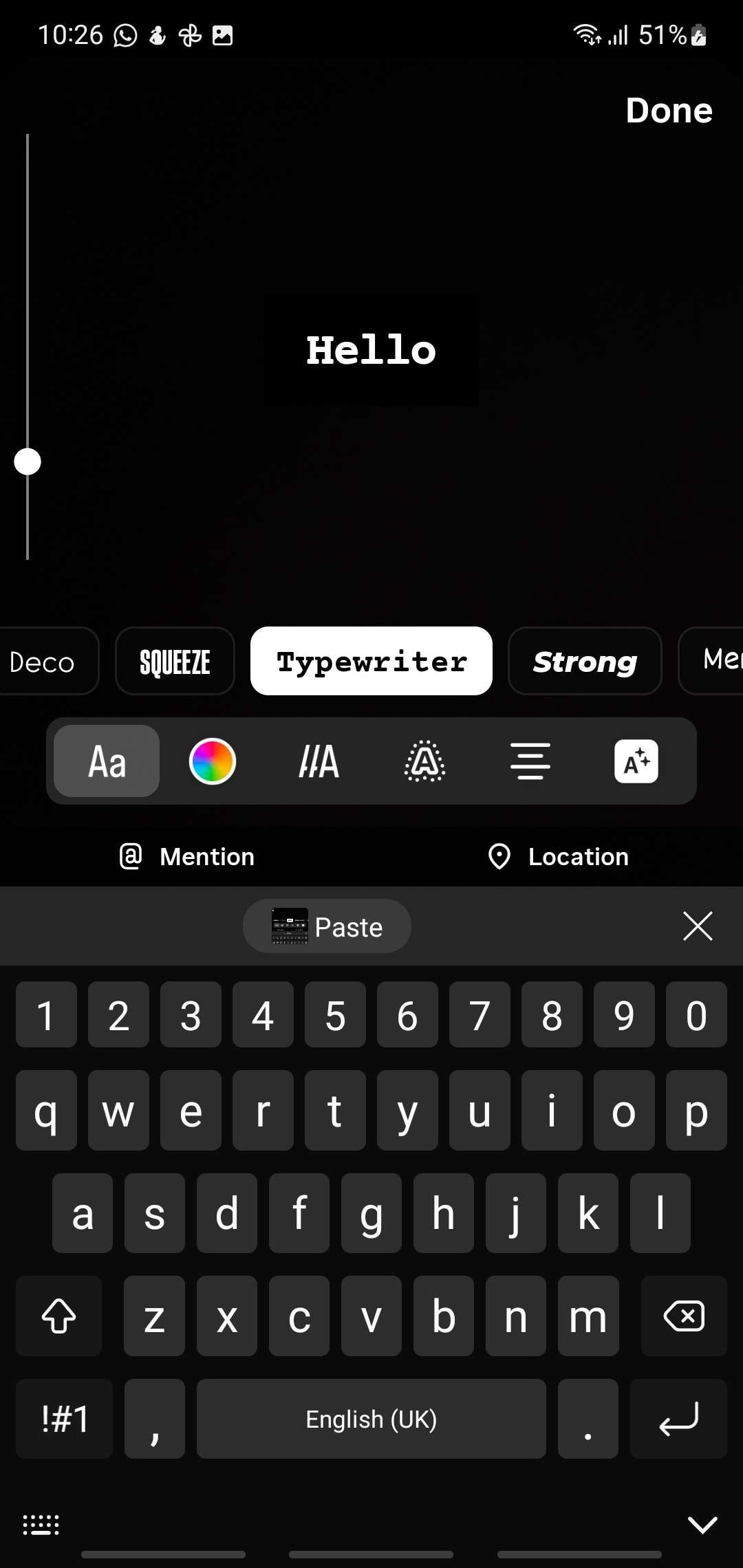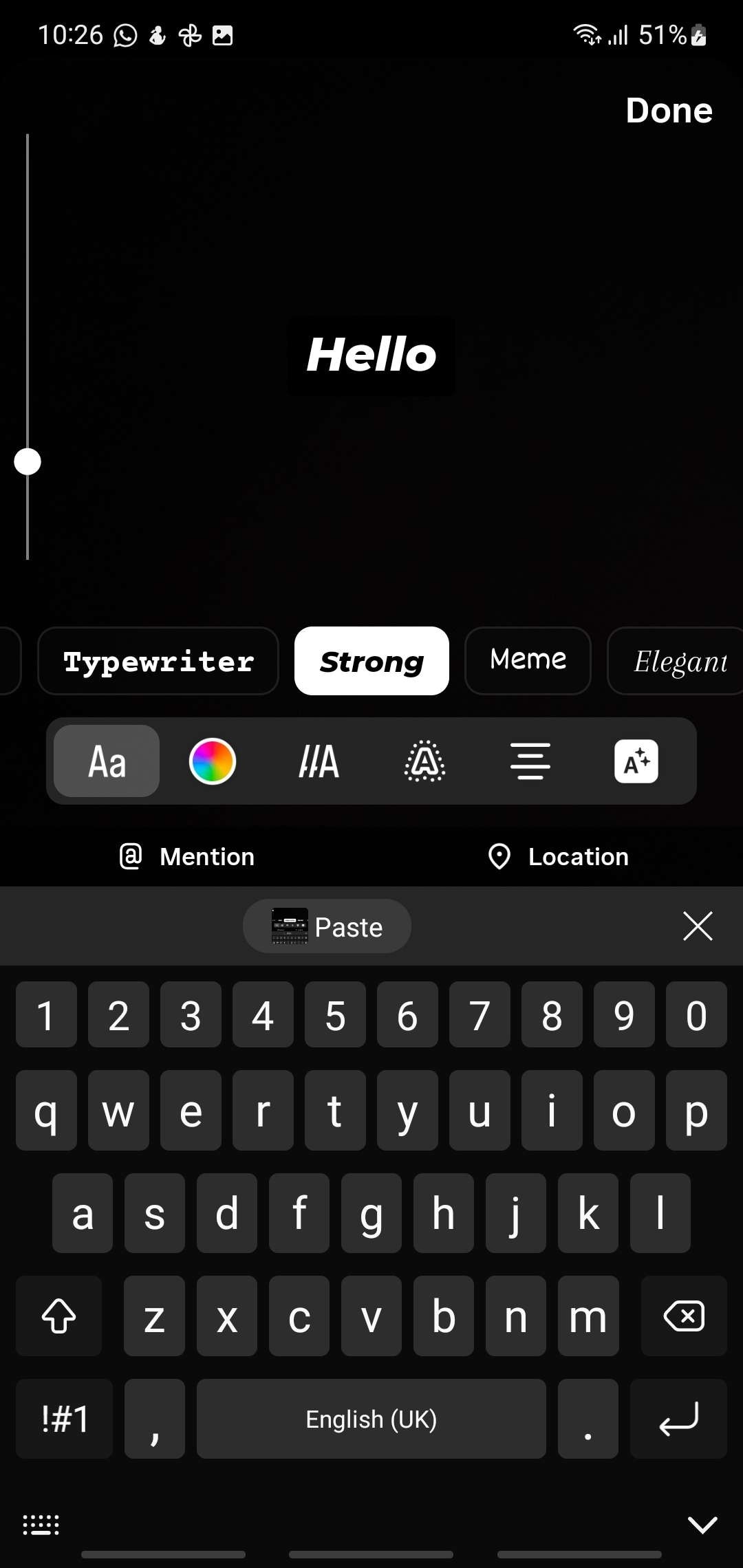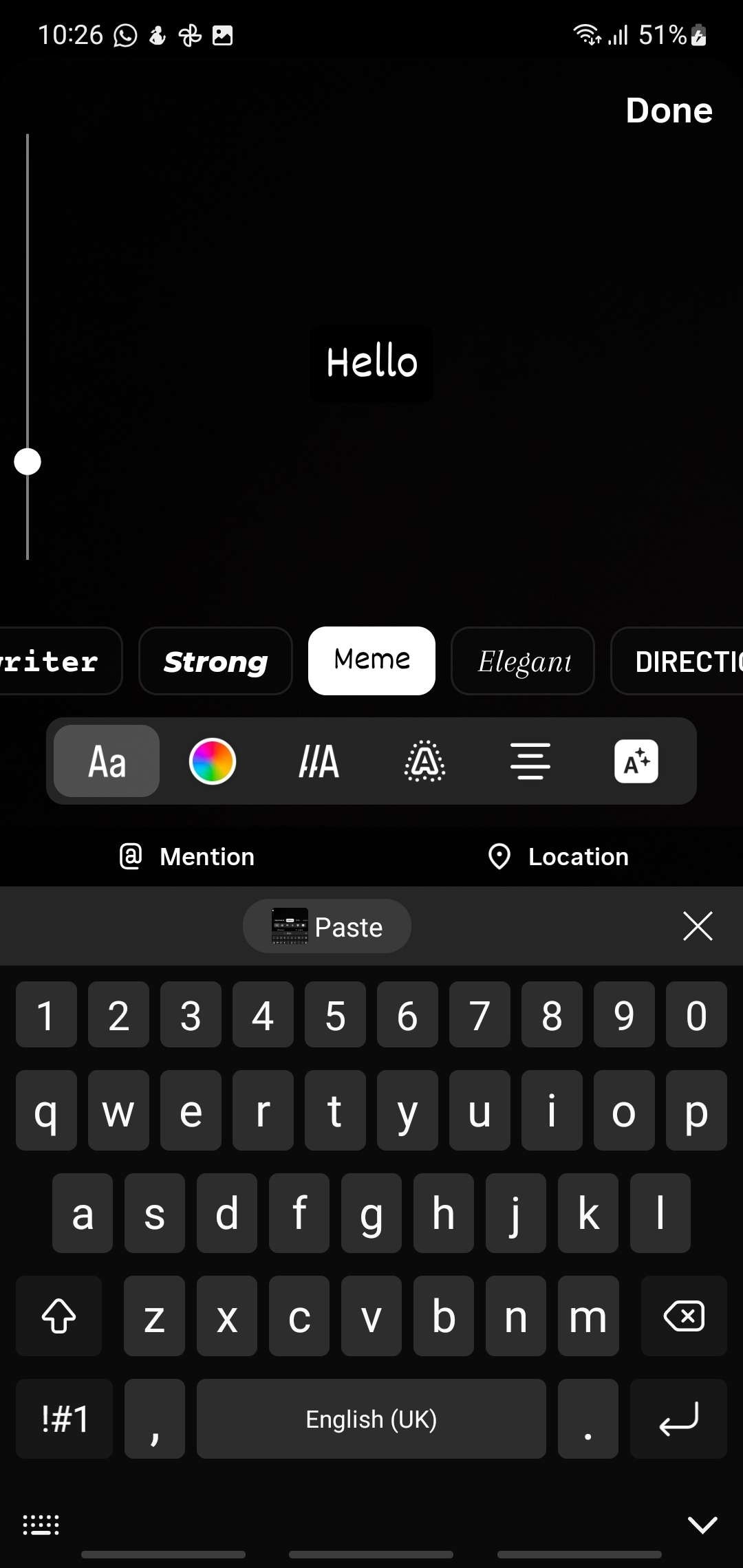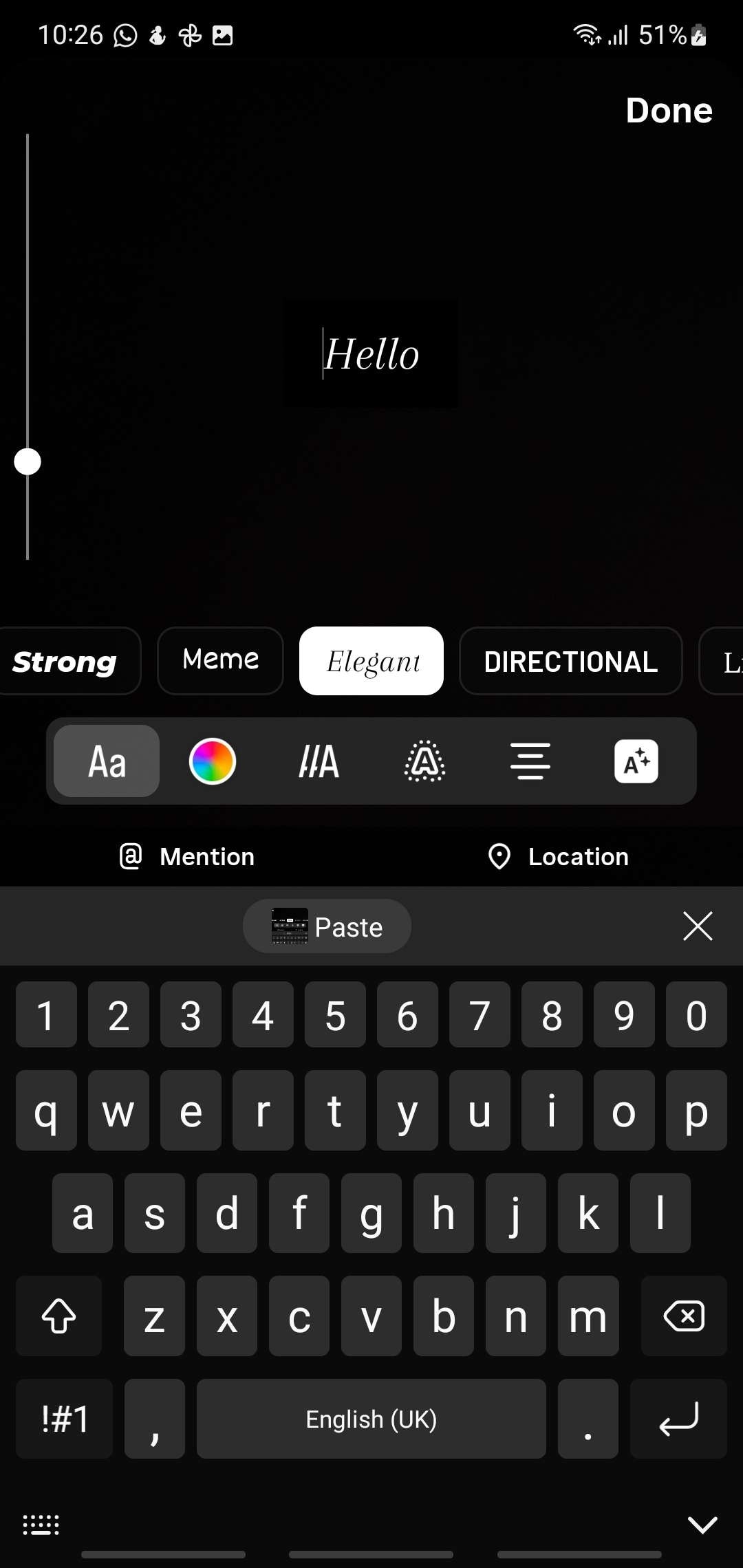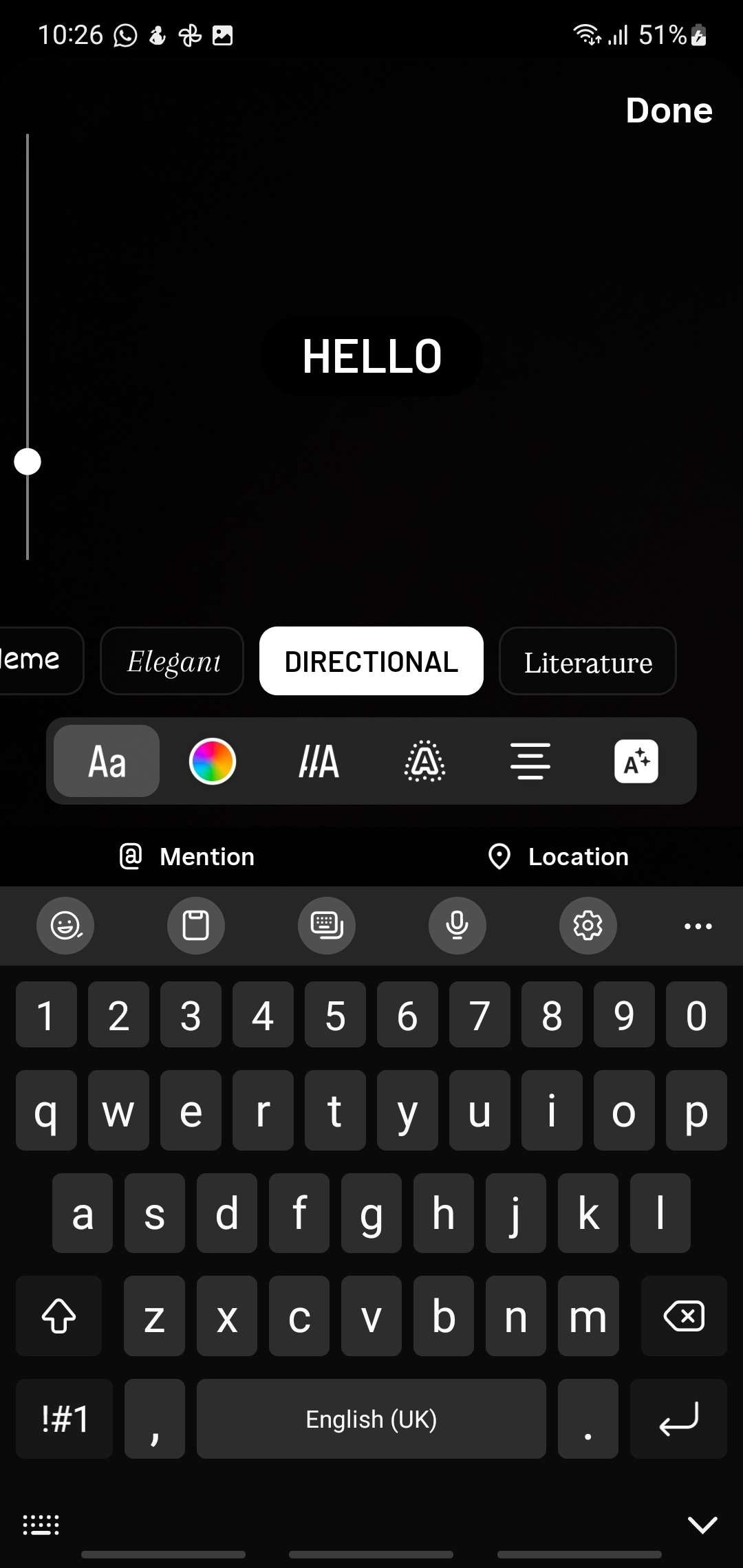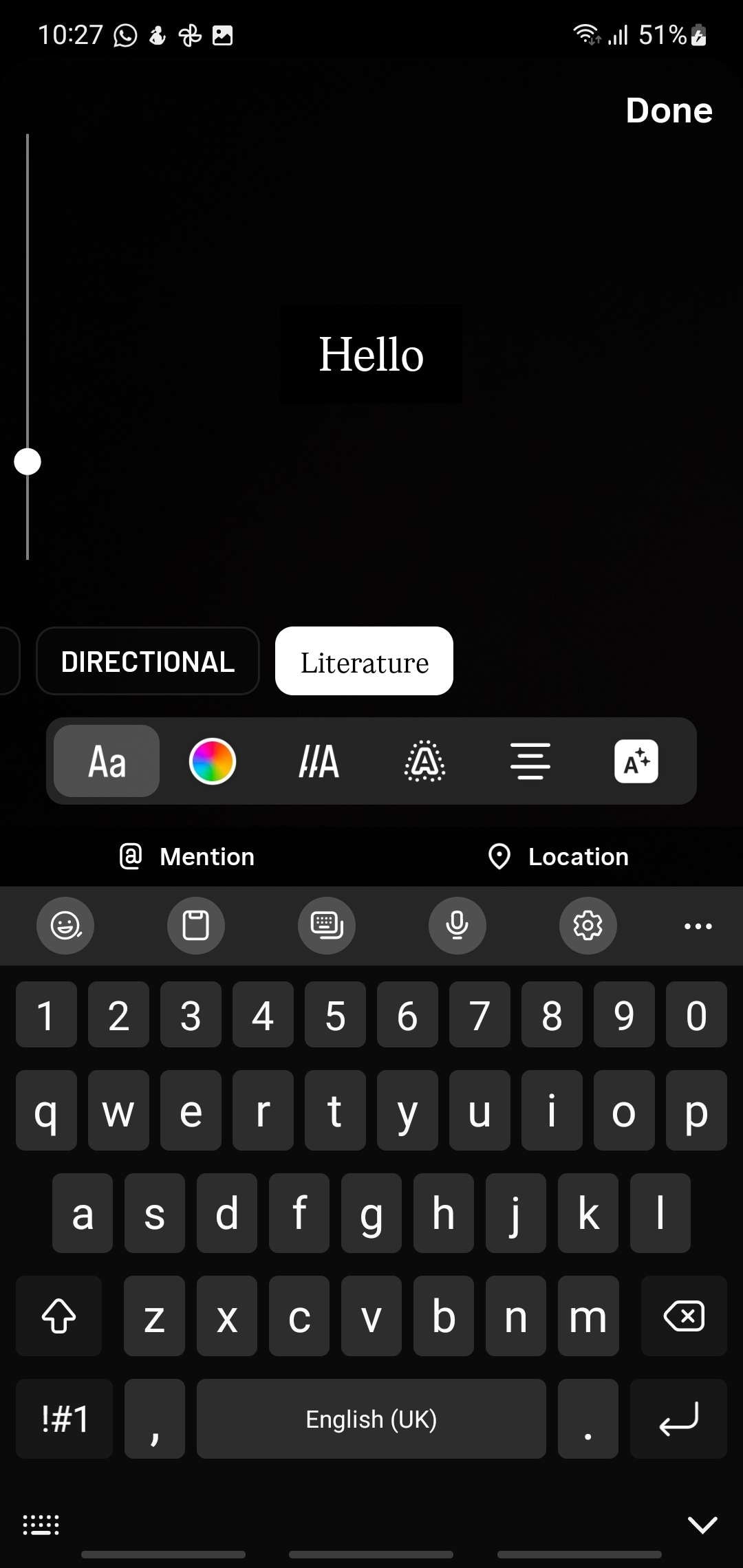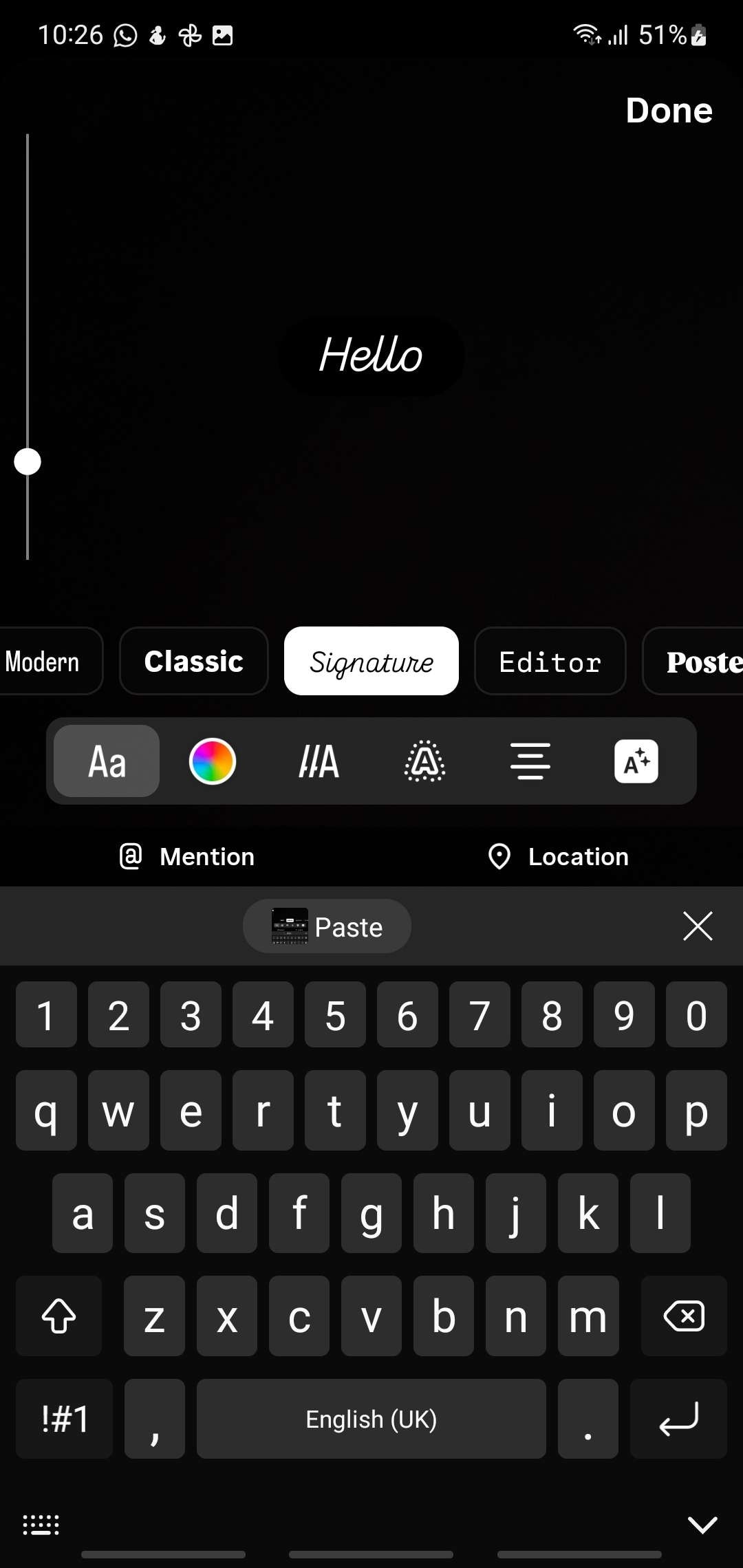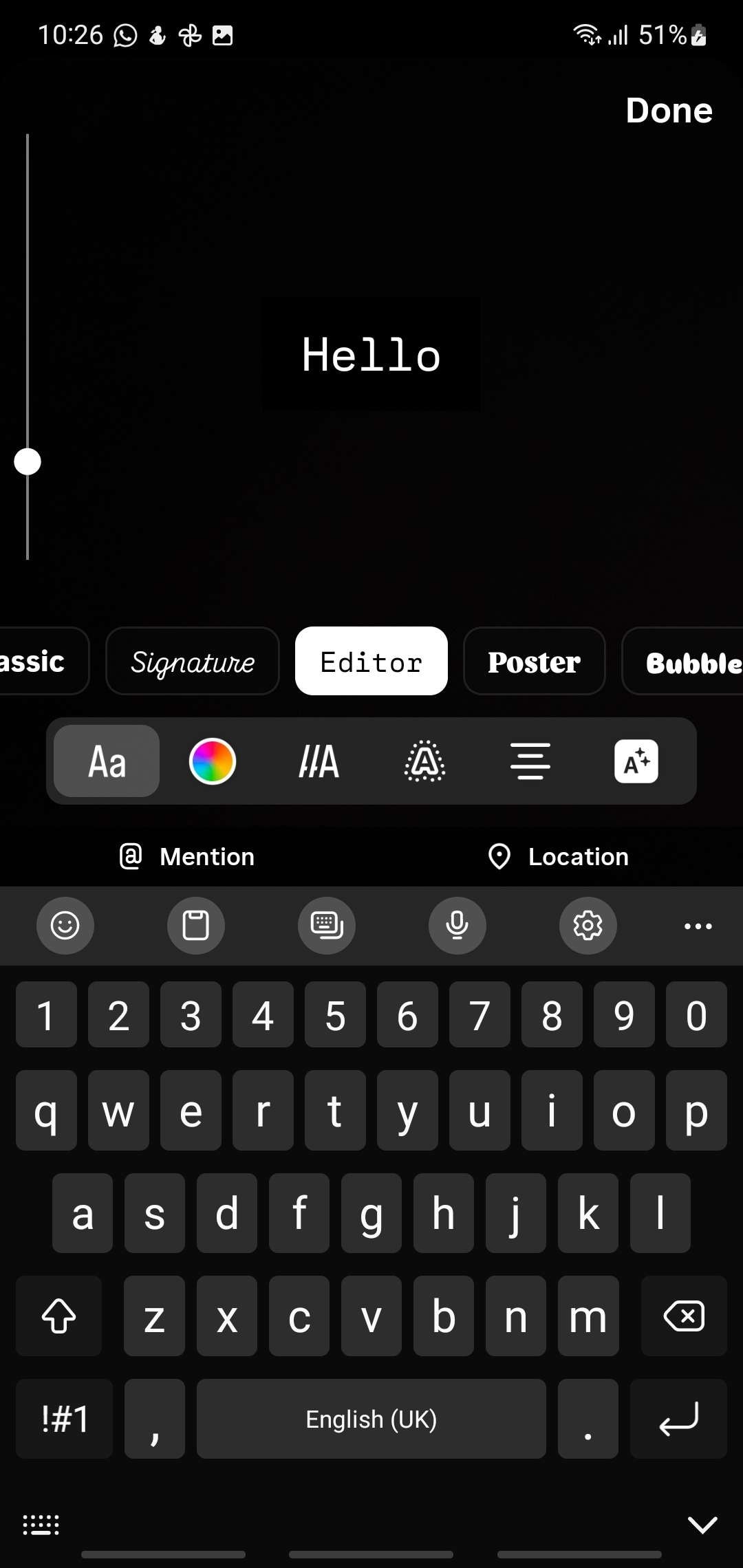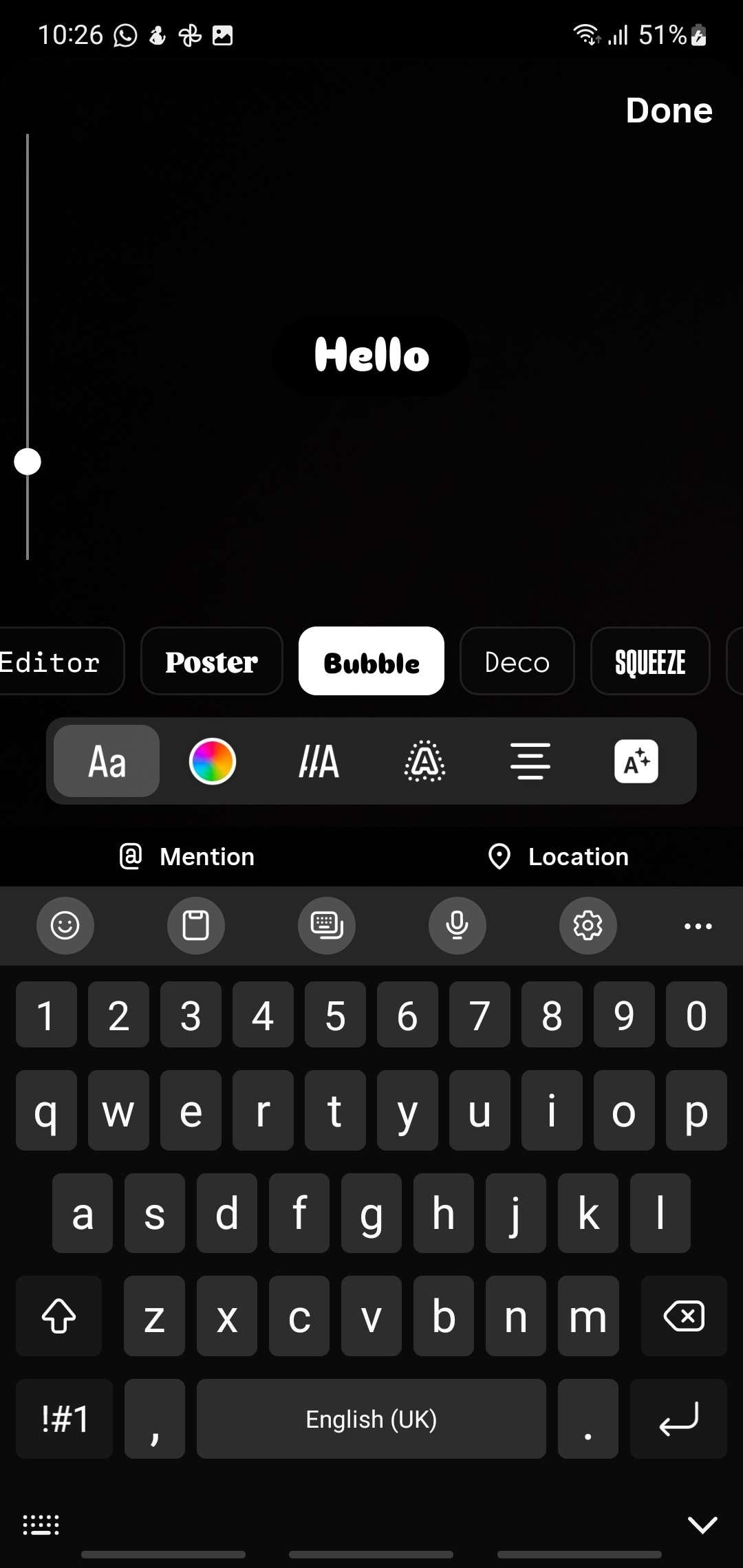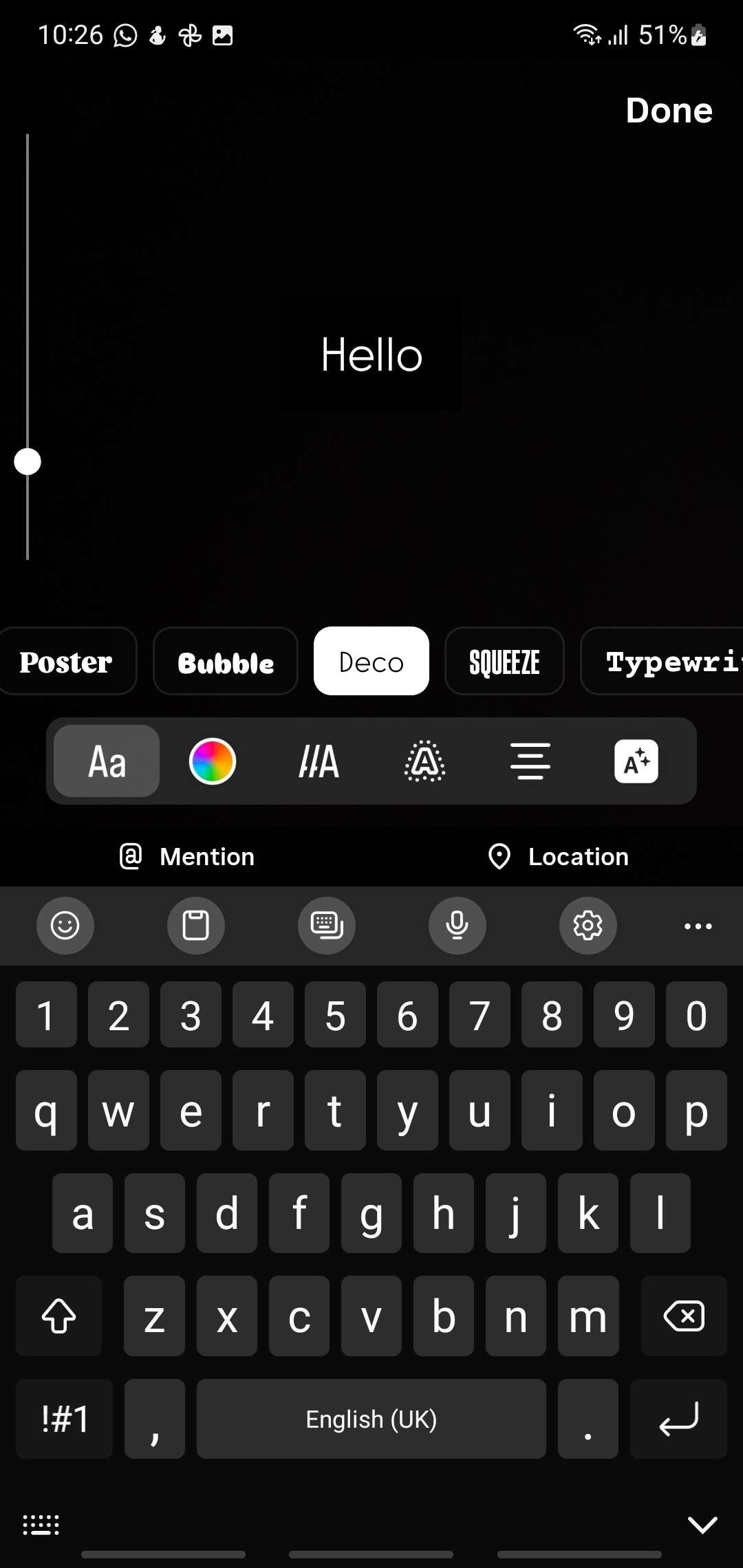
Fontes para Stories do Instagram: Como Mudar e Usar Diferentes Estilos de Letra
Você acabou de lançar um novo produto e quer anunciá-lo no seu story do Instagram. Embora as fotos estejam ótimas, a fonte padrão não consegue capturar a emoção e o estilo da sua marca. Muitos usuários do Instagram enfrentam o problema de um conjunto limitado de fontes que não oferece liberdade criativa. Neste artigo, vamos explorar as várias maneiras de personalizar as fontesdos stories do Instagram, tornando seu conteúdo mais atraente.
Parte 1. Descobrindo as Fontes Nativas do Instagram Para Stories
Além de conhecer os passos para mudar suas fontes para Instagramstories, também é crucial familiarizar-se com as diferentes fontes oferecidas pelo Instagram. As fontes clássicas dos stories do Instagram e as que foram recentemente introduzidas são todas discutidas abaixo para ajudar você a escolher a melhor:
1. Signature
Signature tem uma textura cursiva e manuscrita que parece elegante e pessoal. Ela transmite uma vibe íntima e autêntica, quase como se você mesmo tivesse assinado o story do Instagram. Esta fonte funciona bem para atualizações individuais, conteúdo de estilo de vida ou momentos dos bastidores. Também é um ótimo toque para stories relacionados à moda ou beleza.
2. Editor
O Nova fonte do Instagram como o Editor, possui um conjunto de letras limpo e nítido que transmite uma aparência sofisticada. Também carrega uma vibração profissional e polida, o que faz com que o texto dos seus stories pareça organizado e autoritativo. Este estilo é ideal para atualizações de negócios, anúncios de produtos ou promoções de eventos. Também é uma ótima escolha para compartilhar citações ou posts informativos.
3. Bubble
Bubble tem uma aparência arredondada e divertida com um visual marcante que dificilmente passa despercebido. É casual, leve e animada, sendo perfeita para stories mais descontraídos. Esta fonte pode ser utilizada em stories relacionados a celebrações, enquetes ou sessões de perguntas e respostas com seus seguidores. Também é uma excelente opção para atingir o público mais jovem ou para campanhas de marketing divertidas.
4. Deco
Deco é acompanhada por um toque estilizado e decorativo que parece original e fashion. Este estilo de fonte para stories do Instagram é elegante e artístico, podendo ser usado para tornar seu story um pouco mais chique. É eficiente para promoções de eventos, materiais relacionados a casamentos ou lookbooks de moda. A Deco pode ser usada quando você precisa que seus stories tenham uma aparência fashionista e singular.
5. Poster
Esta fonte é mais apropriada para fazer anúncios, promoções de vendas ou quando se trata de destacar detalhes essenciais. É fabulosa quando você quer criar uma impressão significativa em poucos segundos. A Poster apresenta um estilo de fonte negrito, forte e em bloco que chama a atenção do espectador de imediato. Tem uma aparência sensacional e cativante, fazendo com que sua mensagem não possa ser ignorada.
6. Squeeze
Squeeze é uma fonte para Stories do Instagram estreita e condensada em textura que possui um visual único. A vibe urbana, crua e descolada é geralmente elegante e contemporânea por natureza. A fonte pode ser usada em promoções musicais, convites para eventos ou posts com design simples. Também pode ser útil em stories quando o espaço é limitado, mas você precisa que seu texto seja visível.
7. Classic
A textura da fonte Classic é tradicional, básica e fácil de ler. Sua atmosfera é simples, o que permite que seja flexível e funcione com praticamente qualquer tipo de story. É fantástica para usar em atualizações do dia a dia, legendas descontraídas ou sobreposições de textos que precisam ser claros. Quando você precisa de boa legibilidade e nada mais, simplesmente use a fonte Classic.
8. Modern
Modern é acompanhada pelo visual de linhas limpas com uma textura contemporânea, que é fresca. Ela tem um sentimento chique e descolado, que funciona bem com tendências de design minimalista. Este estilo de fonte para stories do instagram ficaria ótimo em marcas de moda, viagens ou promoções de produtos elegantes e regulares. Também pode ser útil ao trabalhar em templates de stories que precisam parecer profissionais.